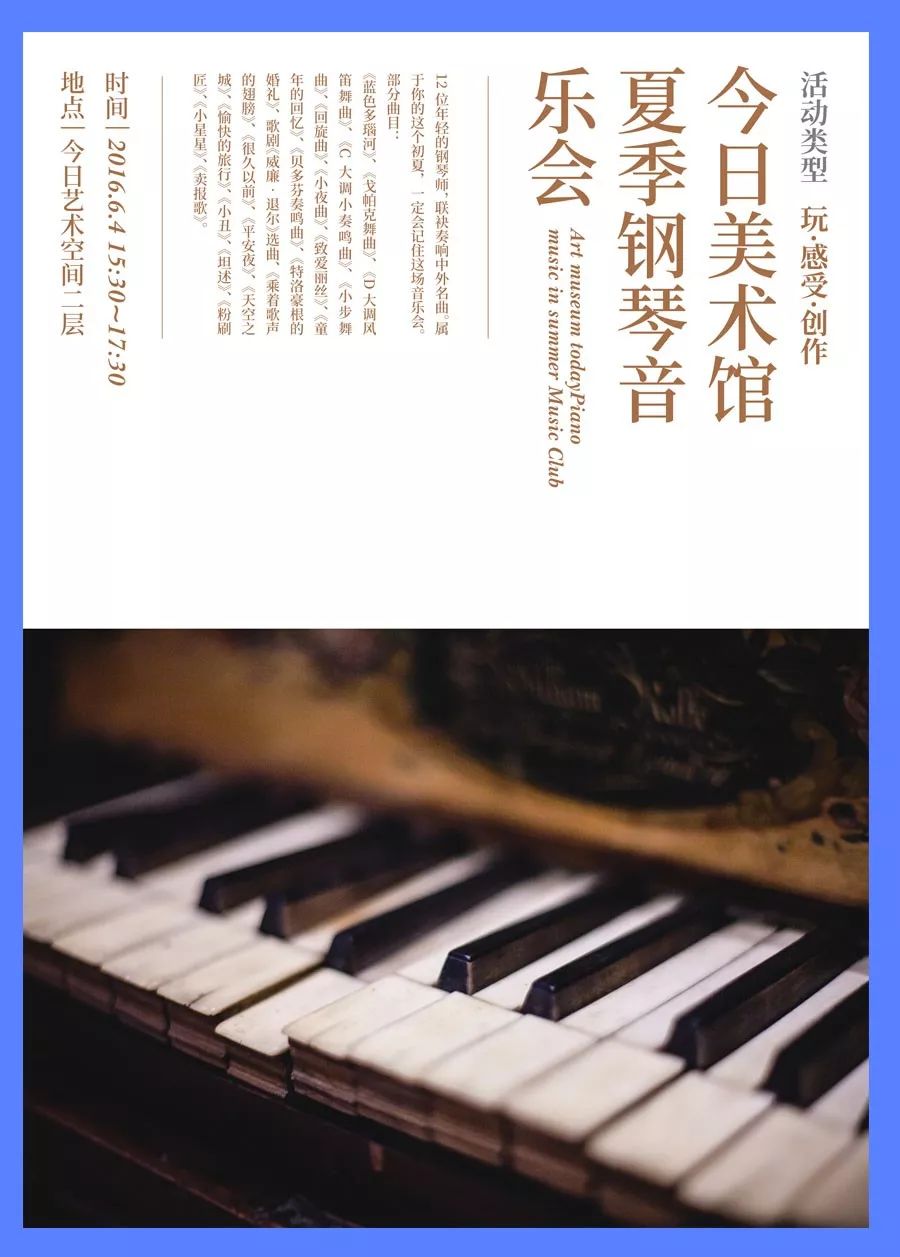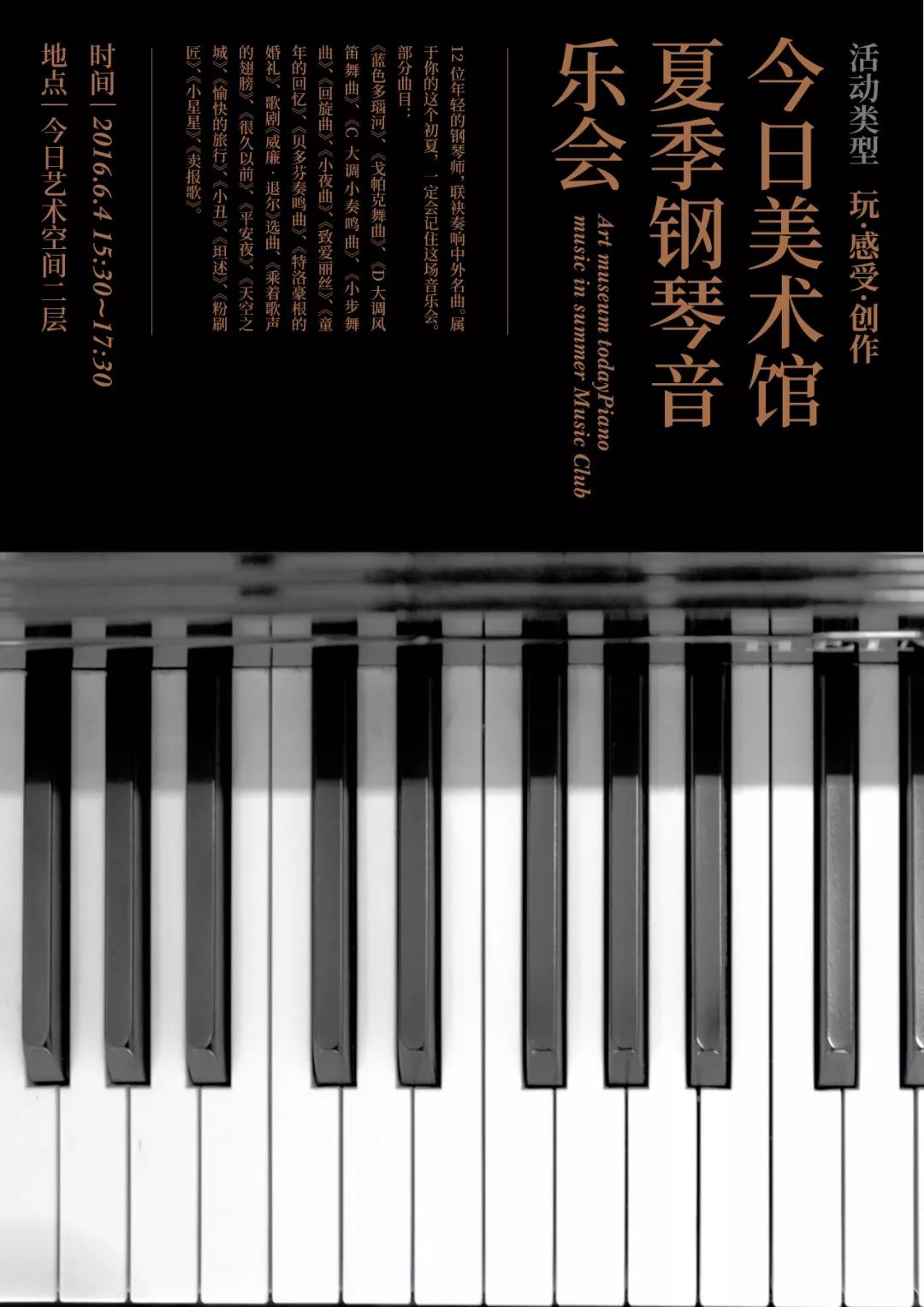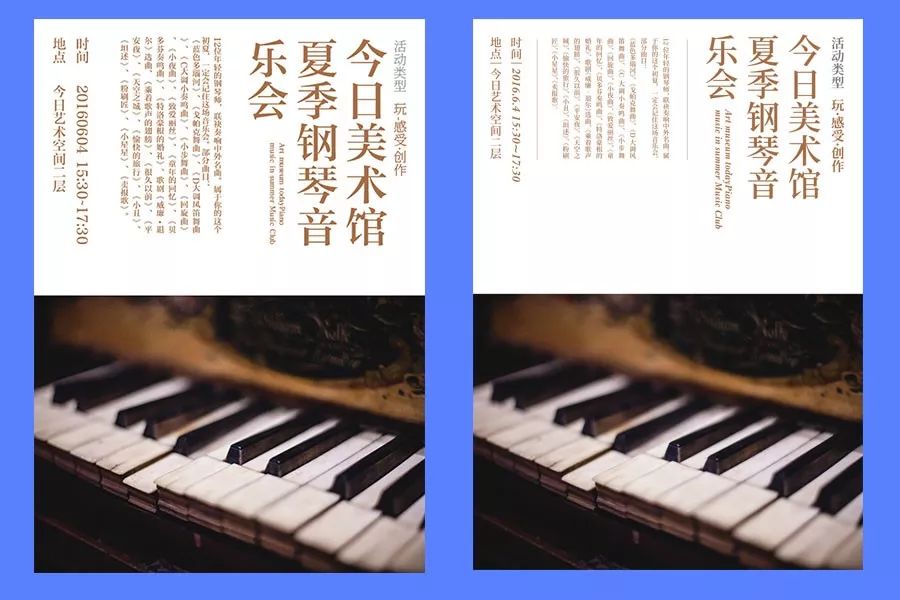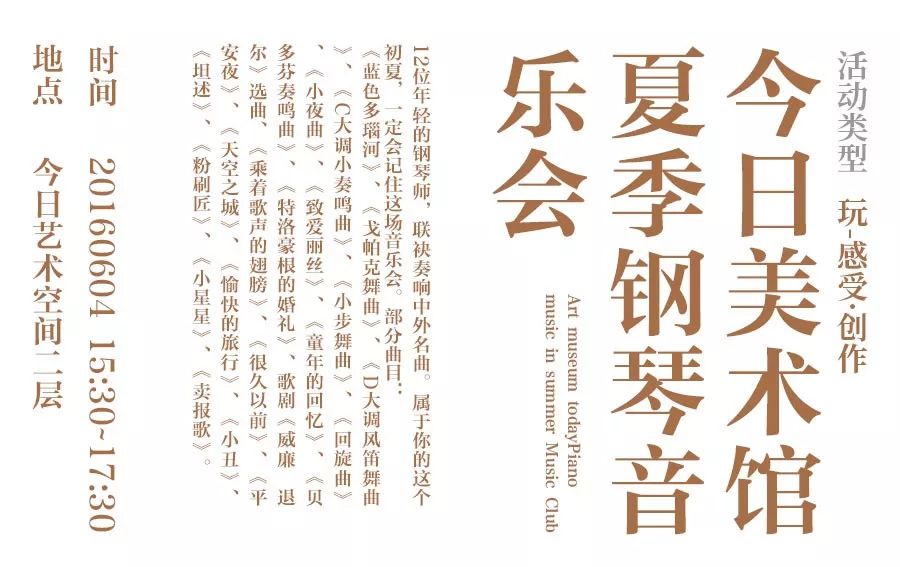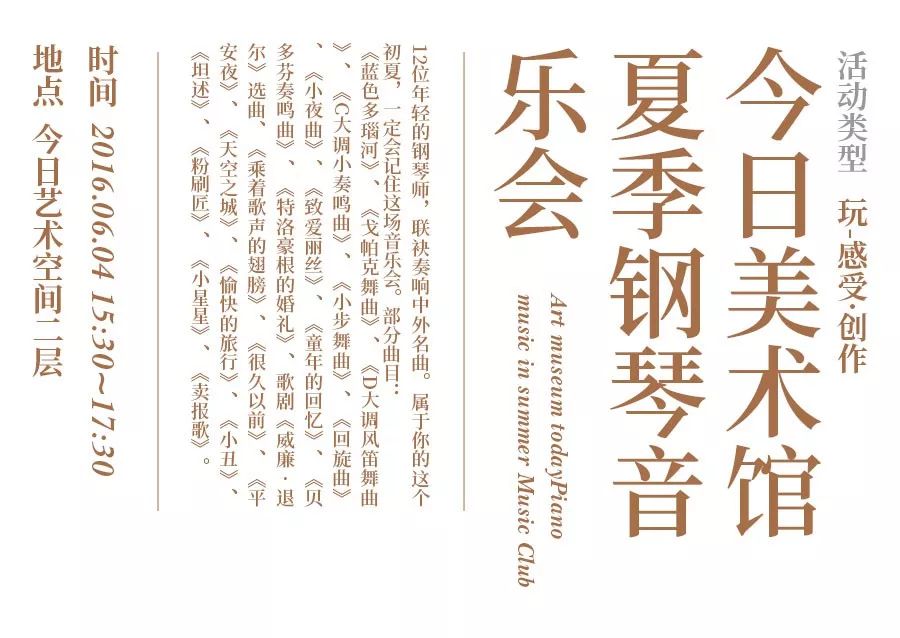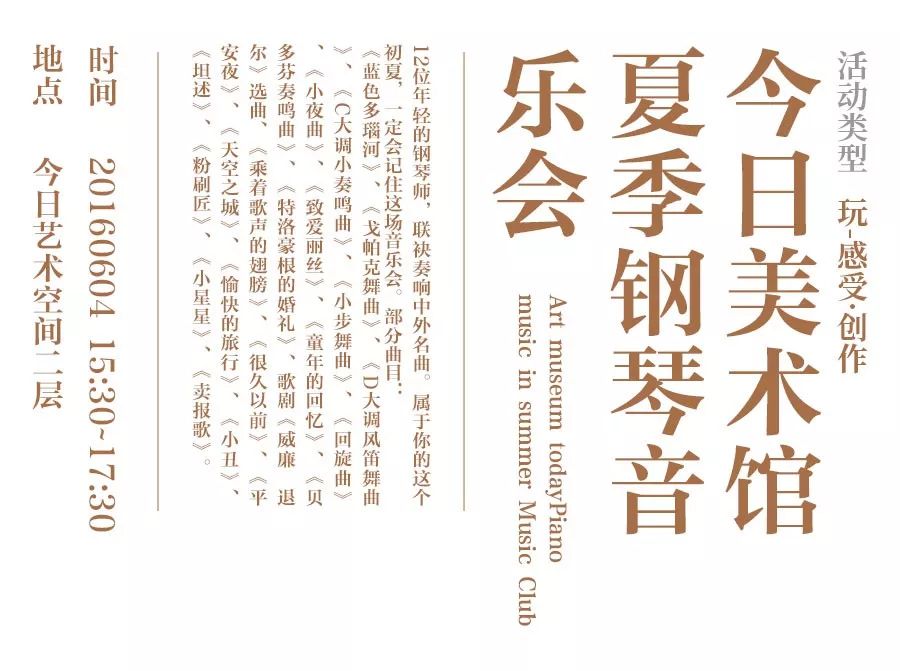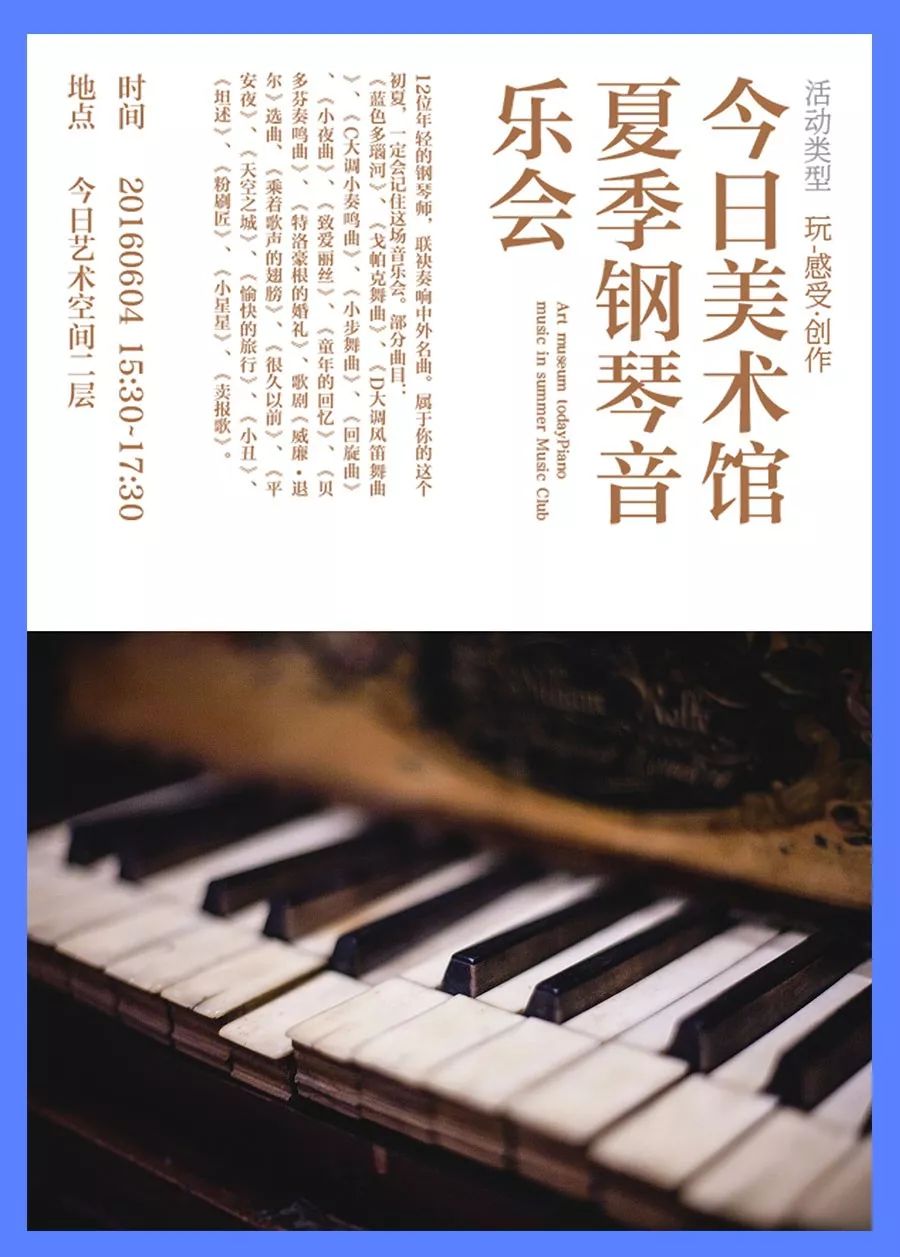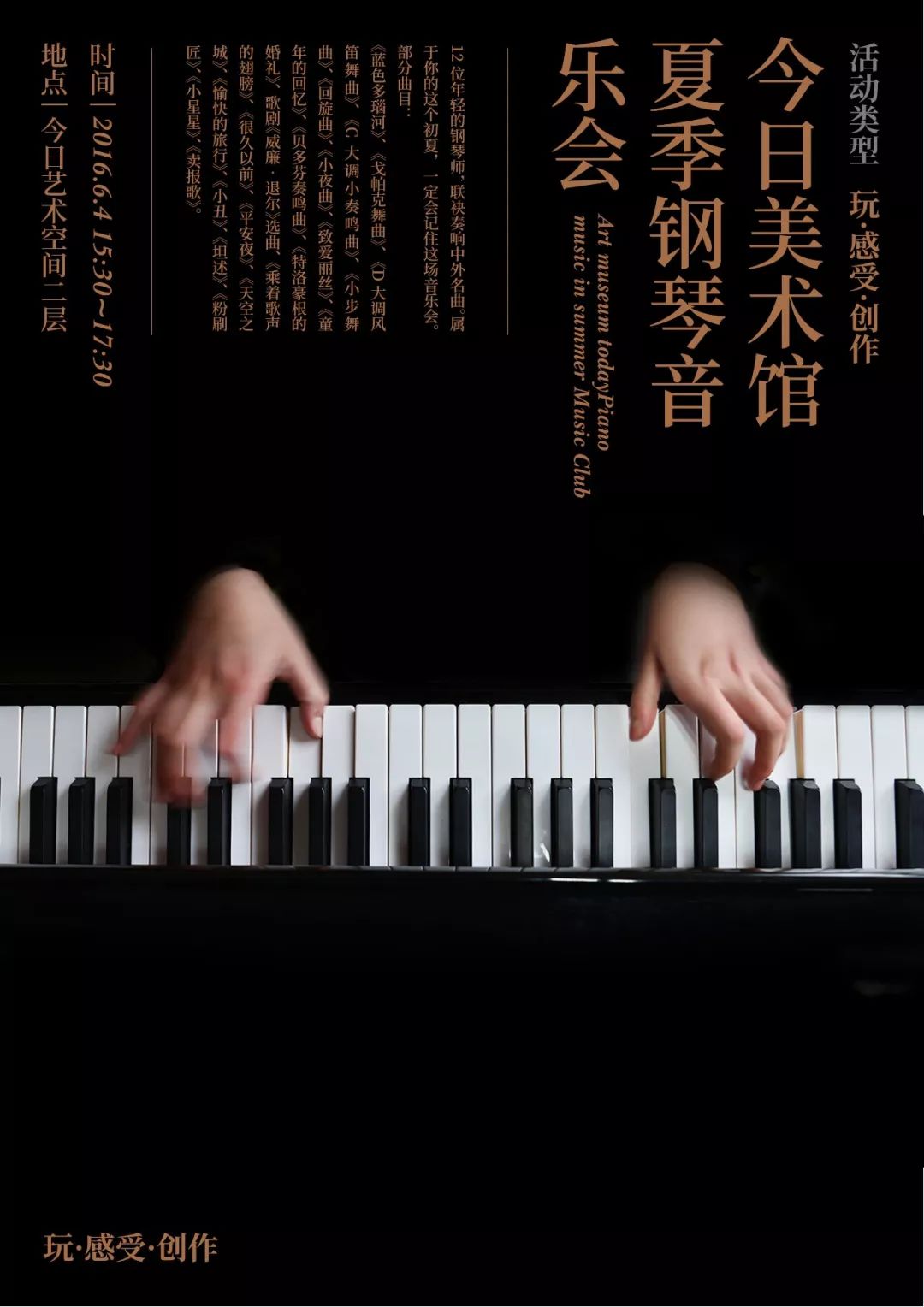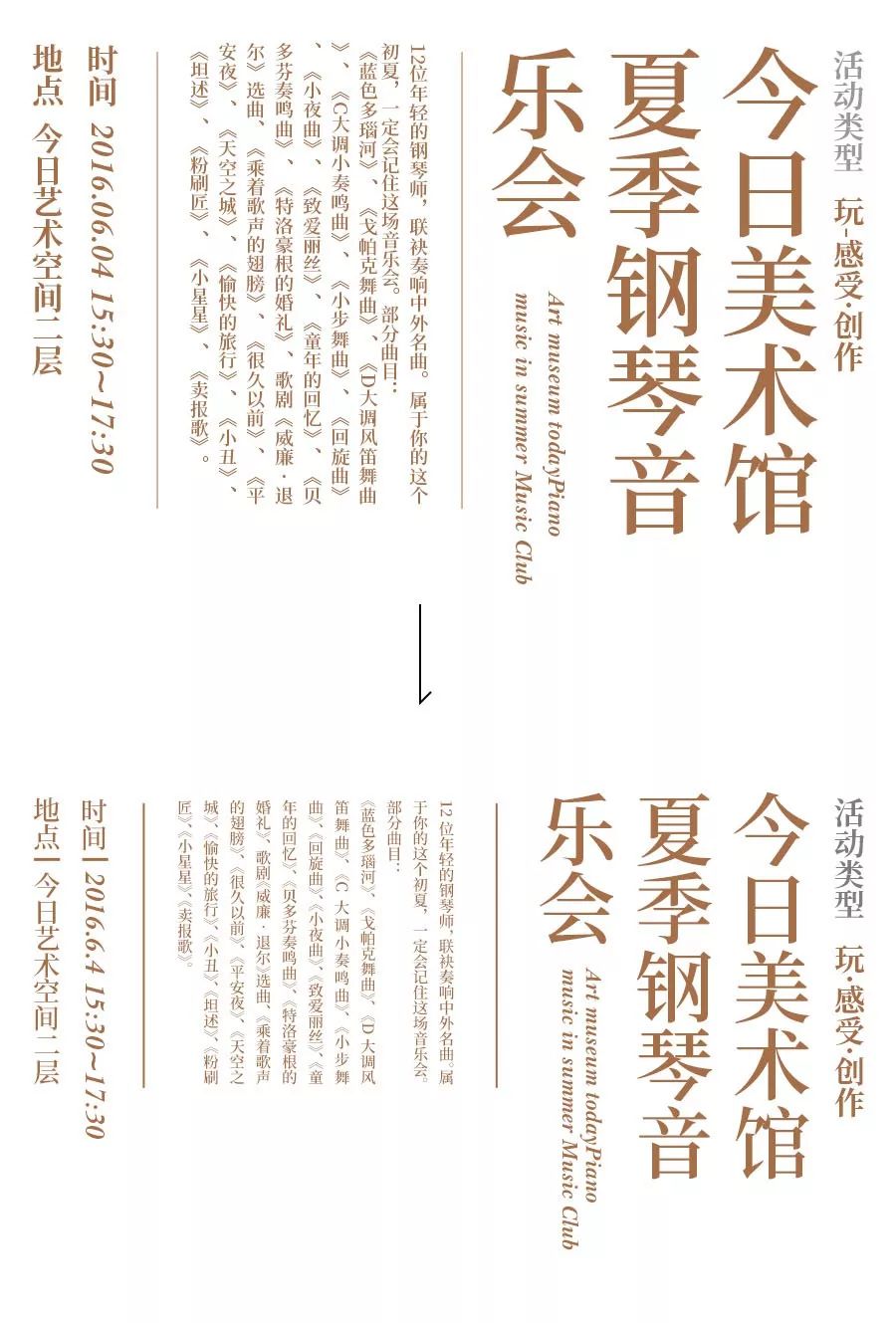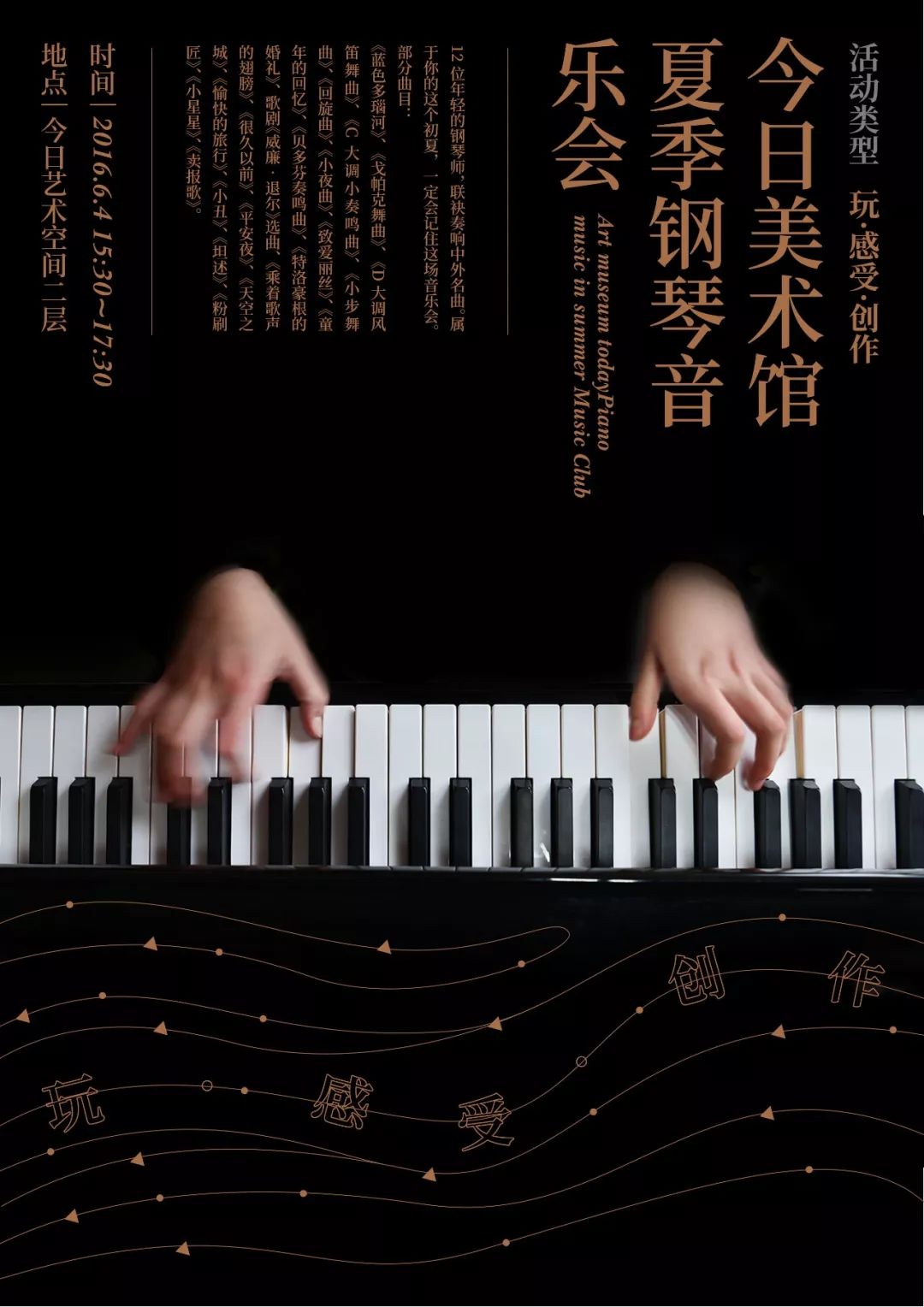
从主体和编排看版式设计
本周给大家带来一篇版式设计的文章,本期的侧重点在于主体和编排。
其实做一个相对来讲比较合格的版式,无非就是这两点,即好的主体与好的编排。
好的主体,即精致美观的主体。
在版式中主体的好坏对版面的影响是非常大的。所以在选择主体的时候一定要谨慎。那么什么才是好的主体呢?
好的主体无外乎有足够的分辨率、独特的造型视角,以及丰富的表现力(质感、光影、纹理等都可以算在表现力之中)。
分辨率高,即选做主体的图尺寸一定要够(不止是主体,其他的图也是越清晰越好)。分辨率不够或者有锯齿的图片一定不要用。
以此图为例,左侧的苹果非常糊,分辨率不够,其视觉效果就比右侧的差很多。
其二就是独特的视角或造型,选主体尽量选新颖的造型或独特的视角,这样会使版面的冲击力更大,同时也更吸睛,达到的效果是事半功倍的。
同样是建筑海报,右侧的要比左侧的好很多,究其原因就是视角的问题。左侧的图片不能说不行,只是视角太常见了,论独特性和设计感远没有右侧仰视视角好。
其三就是主体的表现力,质感、光影、纹理等等都算是表现力。表现力强的更为吸睛。严格来算的话视角、造型、创意性等都算是表现力。
在此案例中右侧的金属质感更为丰富,所以其品质感和设计感更强,而左侧随手拍摄的就逊色很多。
接下来说一下好的编排是怎么样的。
好的编排实际上就是在编排上要严谨有序。
层次的清晰、字型选择的契合性、留白是否工整、段落文字编排是否适合阅读,这些都是能够影响编排好坏的。
接下来我们以一个海报评改为例分别讲这四点。原海报如下
这个海报在文字编排和主体选择上都有问题,我们先对照知识点看一下文字的编排。
对比合理,文字层级的清晰与否决定着版面的视觉顺序。过大或过小的对比都会使版面的品质感下降。
海报中信息的层级划分是十分明确的,这点没啥问题,但是主标题与底下的英文对比过大了,所以视觉上非常不美观。
鉴于此我们可将英文放大,使其对比的更和谐一点。
除了放大英文,在正文与标题和时间之间加了两条竖线做区分,会是层次关系分的更明显。层次关系处理好后,可以去调整字型。
选择字体也是版式设计中非常重要的环节,不同的字体传达的气质是不一样的,要选择与项目契合且非常精致的中英文字体。
原图中中英文字体用的都是方正中雅宋,中文部分用此字体没啥问题,但英文却不是很精致,所以英文符最好选择英文字体。
修改后中文选择了思源宋体,英文选择了baskervill,其气质更为契合。
下一步是修改段落文字的编排,原先的行间距太密,段落工整,因为顿号太多字距又显得太散,文字也参差不齐,这些都是我们要去修改的。
留白工整影响版面的精致程度,虽然到这里字体选择和层级关系没啥问题,但版面的留白不够,显得太挤太满,所以我们可以适当缩小字体,以留出更多的空间。
修改后的明显空间更工整匀称,同时也更美观。至此文字编排就处理好了。我们把编排好的文字放到原海报上看一下对比效果
虽然现在文字编排更为美观了,但主体并不好,所以要去找一个更好的主体。
这里我选择了一个俯视钢琴的局部,并将背景变成黑色,其设计感一下子就上去了。
也可以选择正在弹奏的图片作为主体,只不过现在有些问题,就是版面底部太空了,这种情况我们可以添加一些与音乐有关的装饰元素,如下
将活动的主旨放大曲线排列并做成描边的形式,使其不是那么抢眼。同时添加曲线和点元素,象征音乐的节奏与高低起伏。另外这些点元素也可以替换成音符哦。